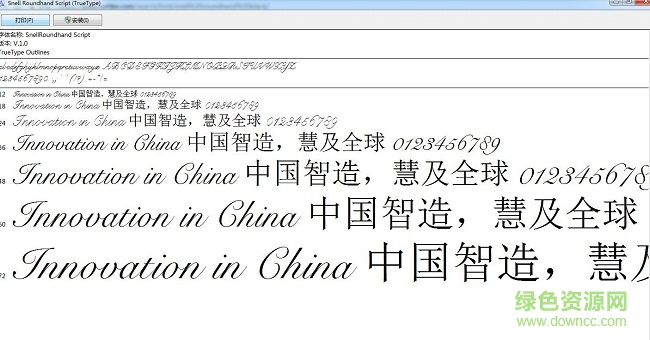
snell roundhand字體是一款英文花體字體,線若游絲,裝飾性強(qiáng),本站為大家免費(fèi)提供snell roundhand script字體以及bold、black、regular等多款字體的合集下載包!
花體是“ornamental penmanship”的不當(dāng)翻譯,英文本意為裝飾性強(qiáng)的寫法,應(yīng)并不特指一種字體。但在歷史使用中“ornamental penmanship”常被用來指稱“斯賓塞”體與其變體?!般~板體”和“斯賓塞體”是兩種相似的字體,都運(yùn)用了裝飾性的寫法。在中國,花體常被用來指稱“銅板體”和“斯賓塞體”。